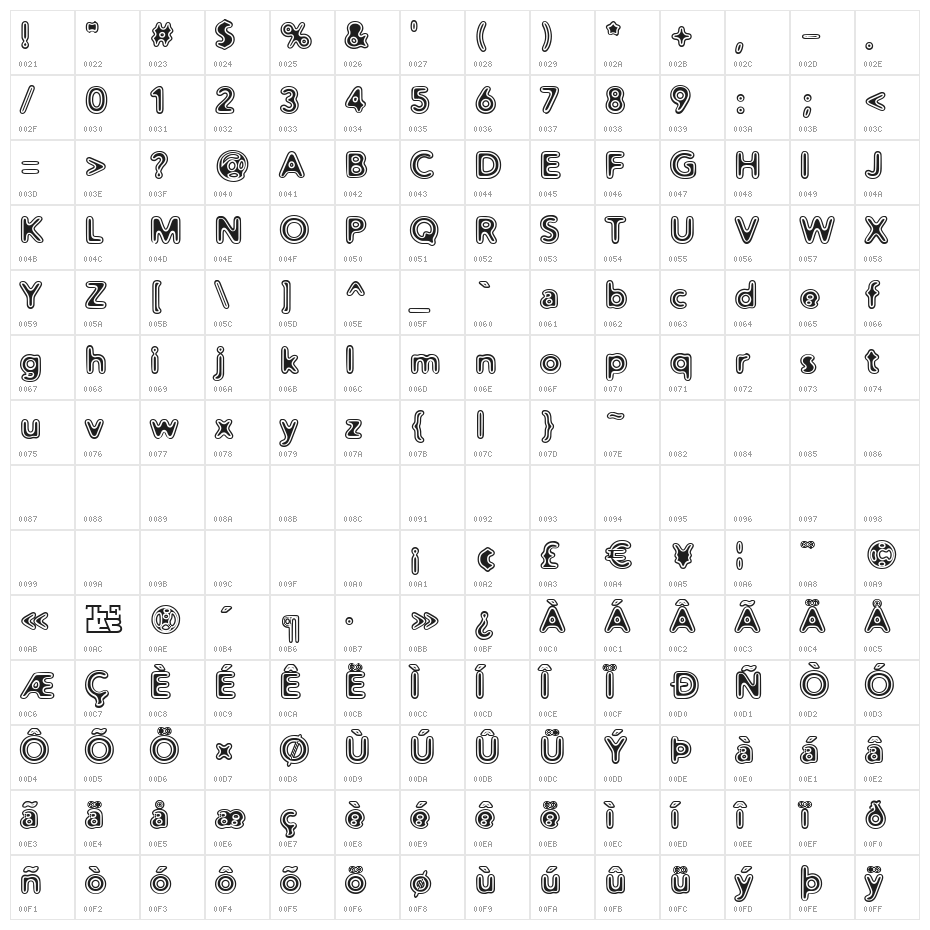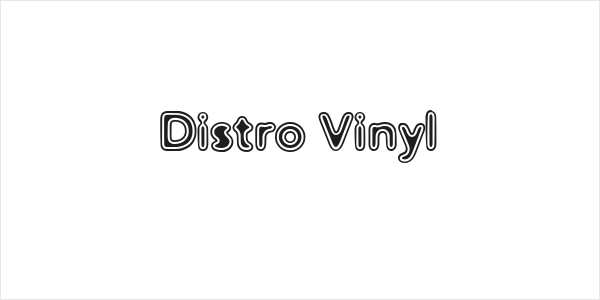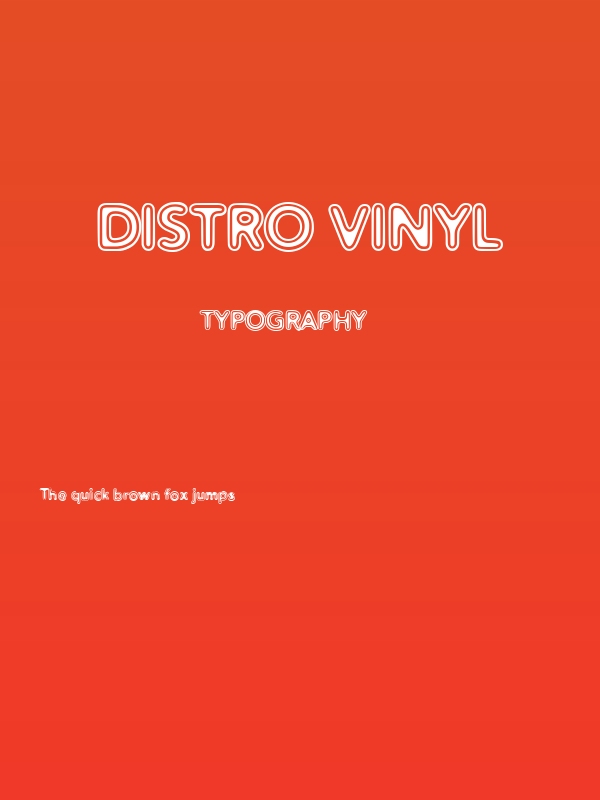
Distro Vinyl Font
| Gesamtstil | Playful, Modern |
| Vorgeschlagene Projekte | Ideal for posters, album covers, children's books, and any project needing a fun, eye-catching typeface. |